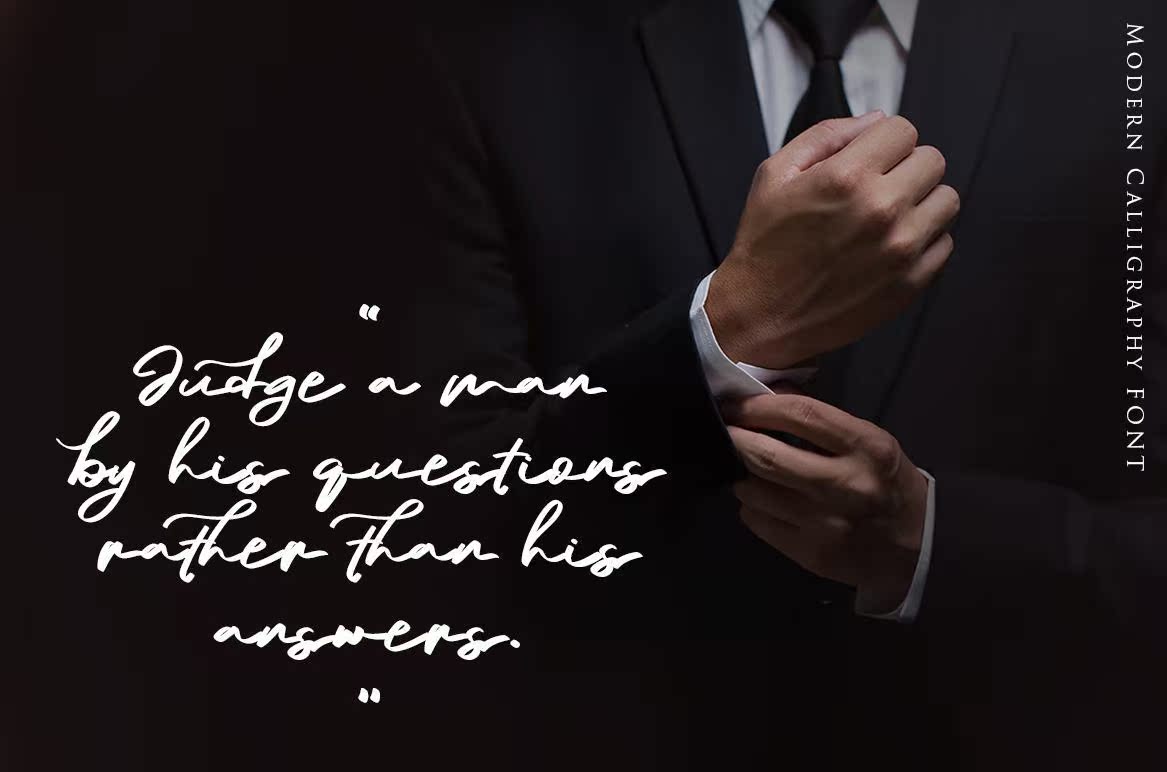
Freesouth Portland Scription Font是一款具有优美曲线和可选字符的现代签名Font。其独特的风格和特征将使您的作品具有个性化。它还与一个正式的文件相配合,您可以安装任何设备。此Font适用于您的项目,包括名片、品牌、标识、海报等。但是,您可以使用此FreeFontonPersonalUseLicense,但是,如果您想获得更多功能!Gopurchasingthepremiumversion。